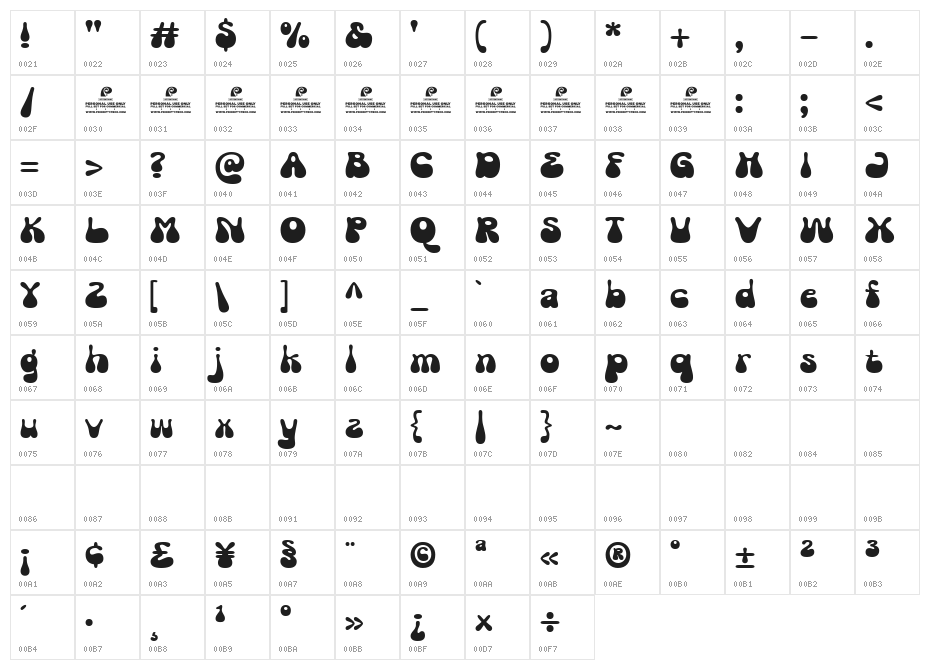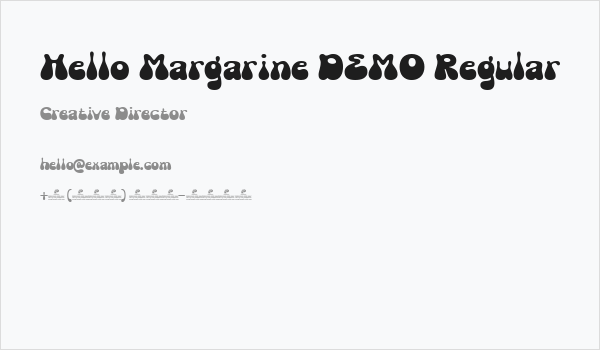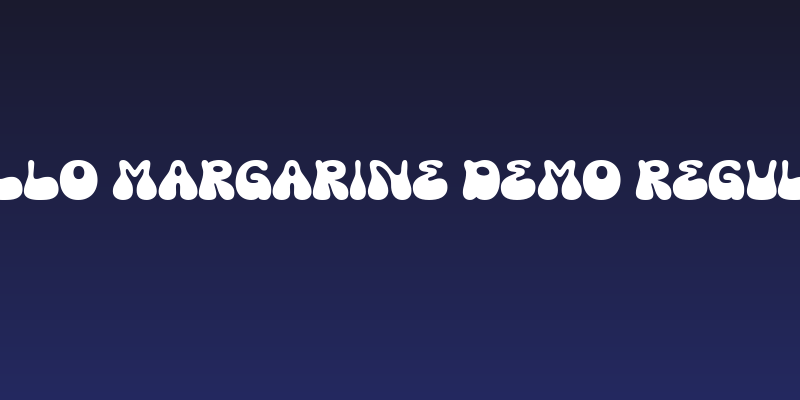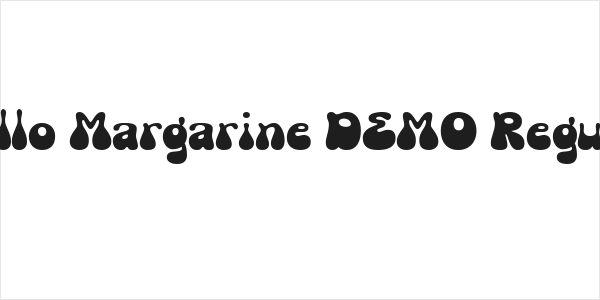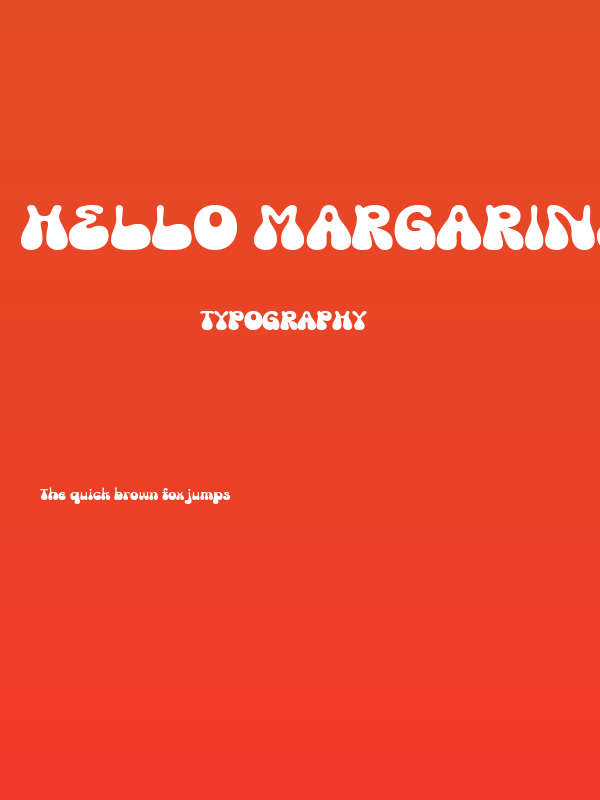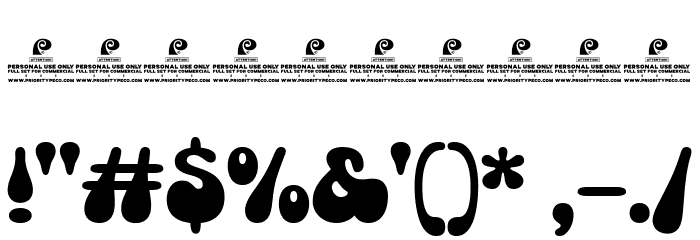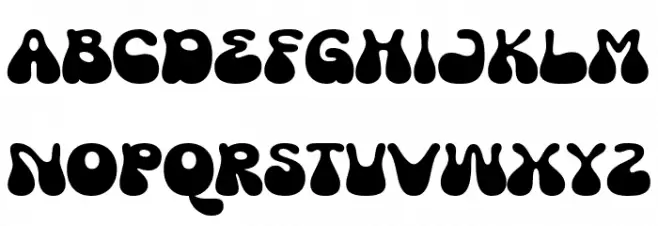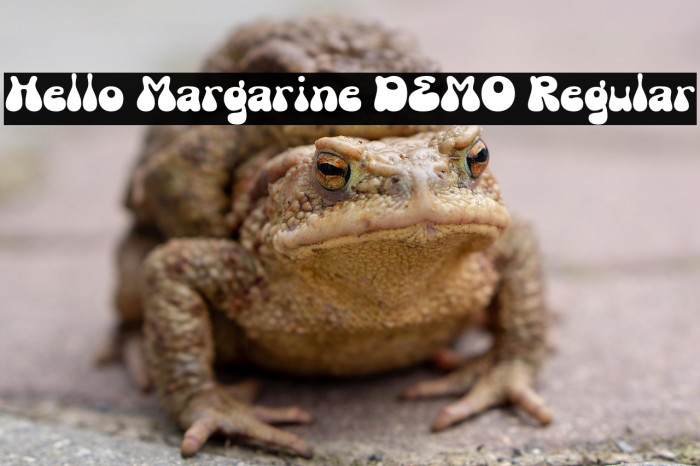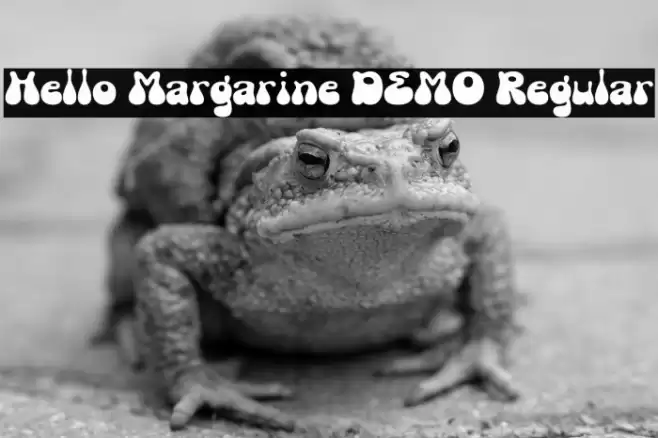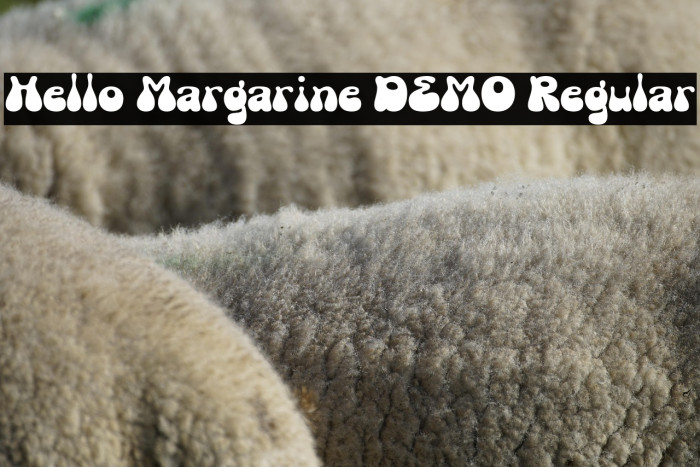
Hello Margarine DEMO Regular Font
| Gesamtstil | Whimsical |
| Anwendungsfall | Logos, Headlines, Posters |
| Vorgeschlagene Projekte | Ideal for children's books, playful branding, party invitations, and creative posters. |